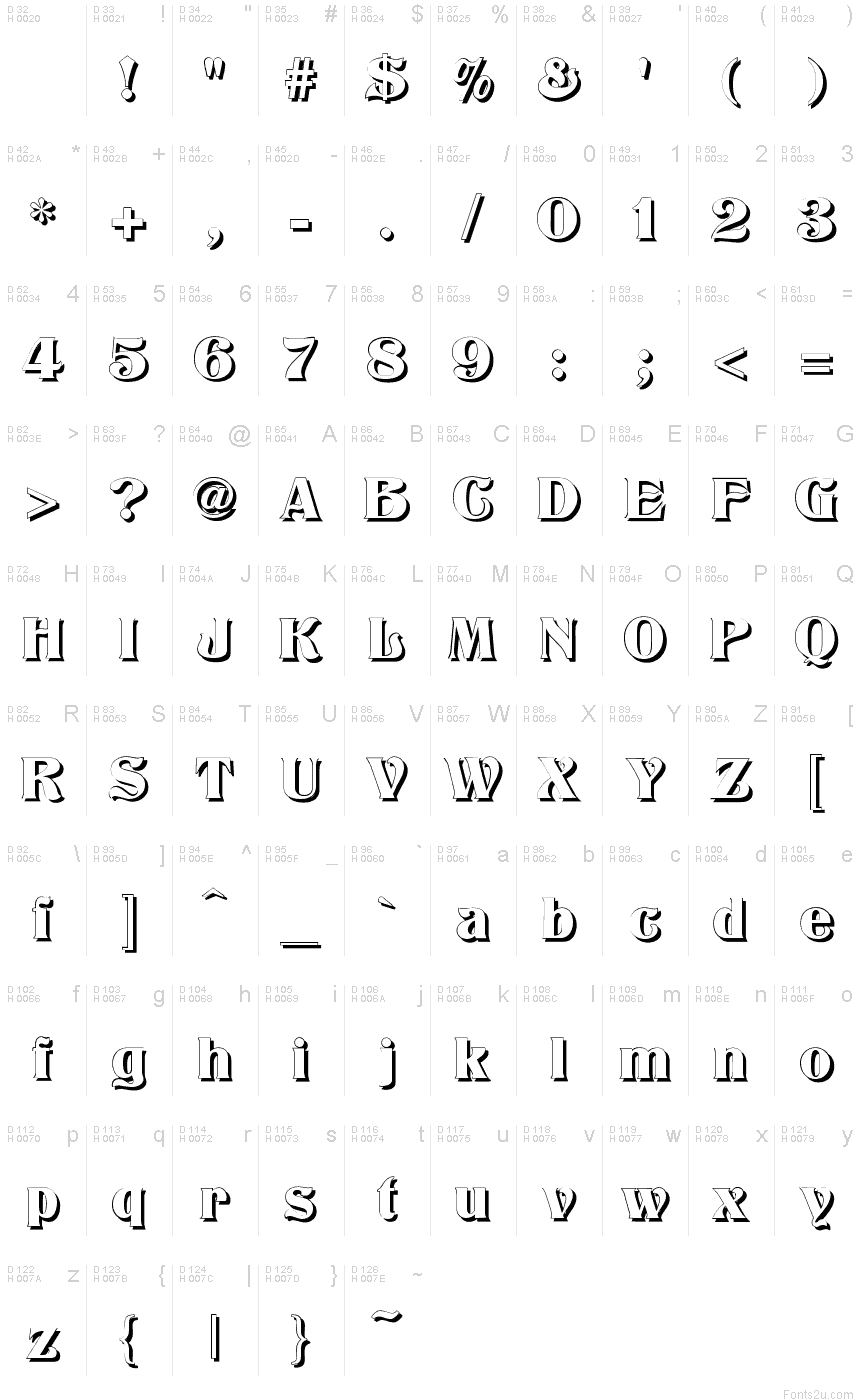
Titania Shadow, darmowy krój displayowy od Typographer Mediengestaltung, nawiązuje do baśniowego stylu szeryfowego dzięki dużym, teatralnym literom i wyraźnemu, przesuniętemu cieniowi. Formy są miękkie i lekko staroświeckie, a nie surowe, więc cień nie sprawia wrażenia sztucznego dodatku, lecz elementu scenicznego uroku liter.
Sprawdzi się na plakatach, okładkach książek, w menu kawiarnianych, na opakowaniach i w grafikach eventowych, gdzie darmowy font może dodać nieco klimatu retro bez przesadnej dekoracyjności. Wykorzystaj go do krótkich nagłówków, tytułów lub inicjałów, gdy chcesz, by warstwowe szeryfy przyciągały wzrok w zwięzłym tekście.